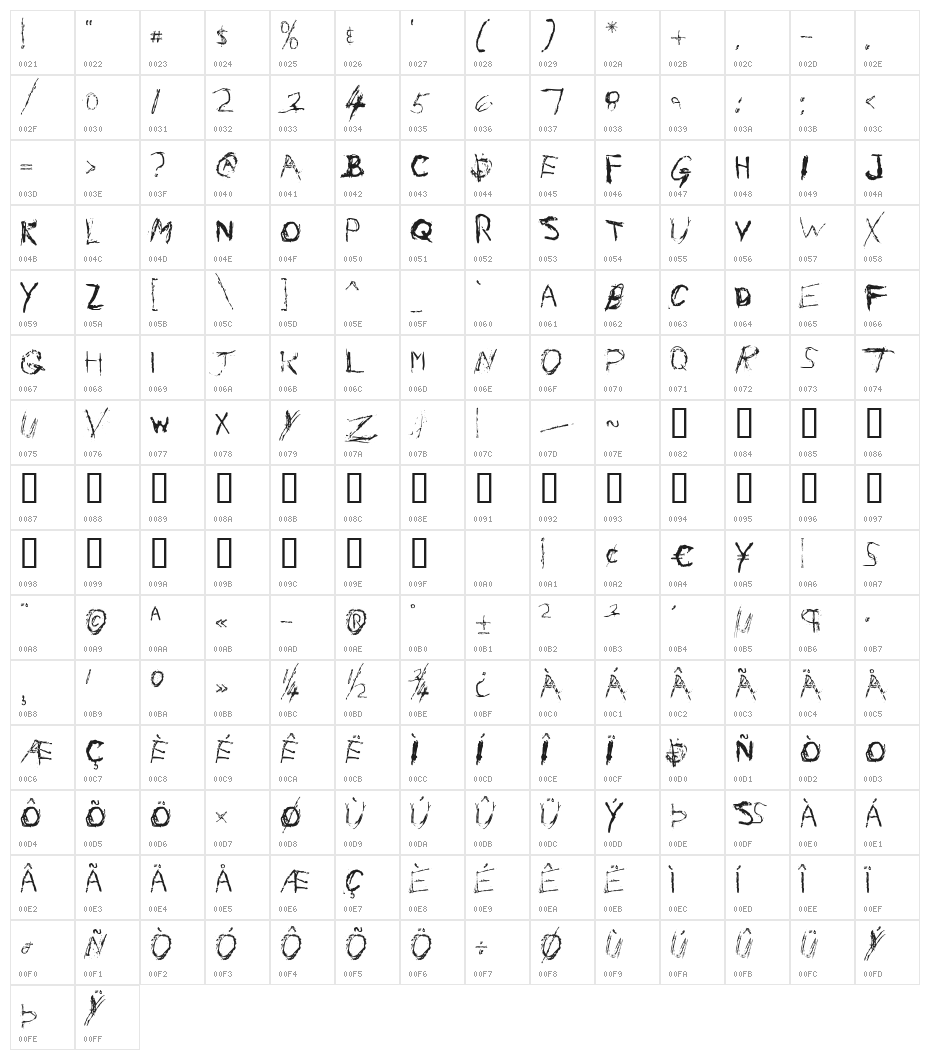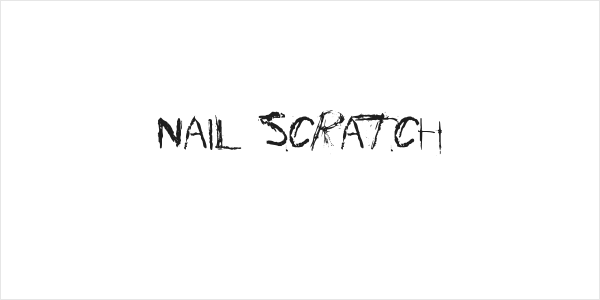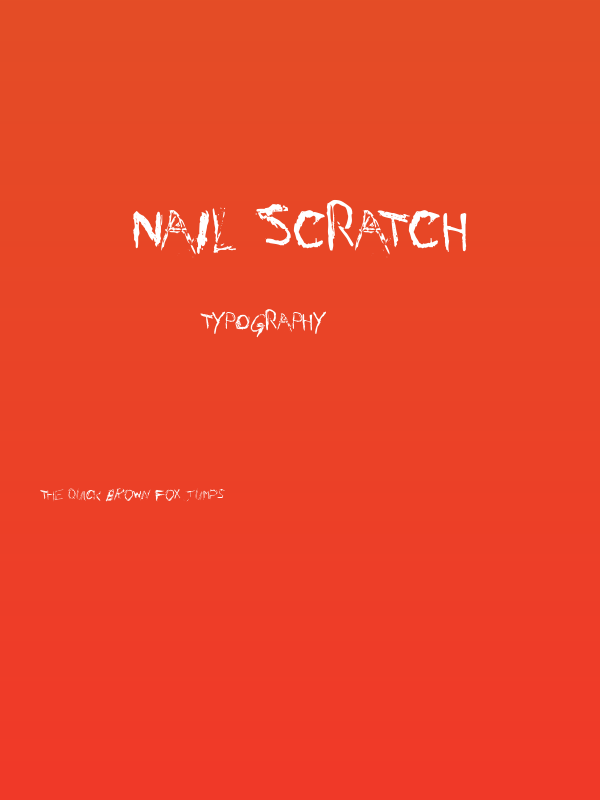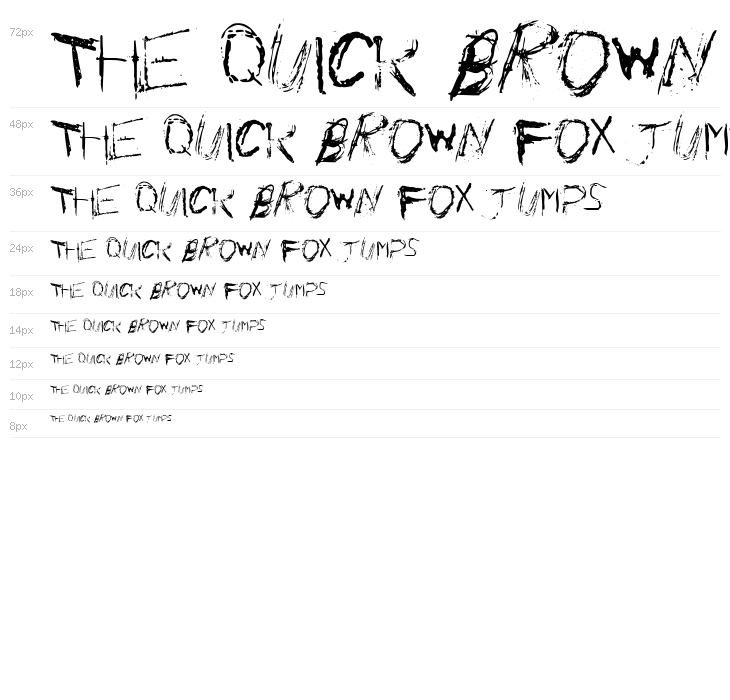
Nail Scratch Font
| Vorgeschlagene Projekte | Ideal for horror movie posters, album covers, street art designs, or any project needing a gritty, rebellious vibe. |